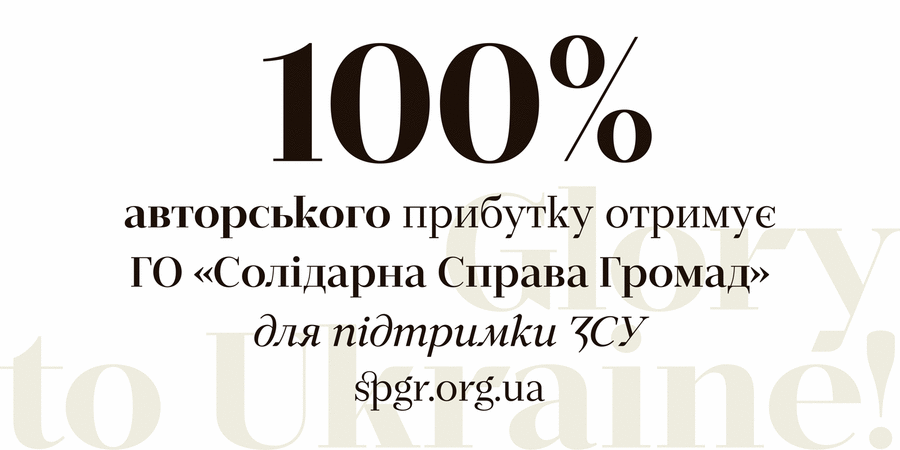
Опис гарнітури IT ExtraziumЕлегантна і брутальна антиква з сильним контрастом. Шрифт призначений для використання в заголовках, логотипах, ініціалах, а також як текстовий у невеликому розмірі (9-10 пт, Regular). IT Extrazium підтримує багато мов на кирилиці та латиниці, має українську кирилицю, лігатури, альтернативні гліфи. Шрифт розроблено Тетяною Іваненко у 2019-2023 році.
Асоціації з сімейством шрифтів IT ExtraziumОсобистість і характер гарнітури:
гламурний, модний, ювелірний, художній, різкий, чіткий, оригінальний, характерний, гордий, цікавий, багатий, дорогий, серйозний, рівний, технічний, сучасний, статичний, культурний, освічений, стійкий, стабільний, твердий, гострий, динамічний, розкішний, сміливий, важливий, сексуальний, колючий, авторитетний, значний, переконливий, драматичний, мотивуючий, помітний, яскравий, активний, солідний, важкий, щільний